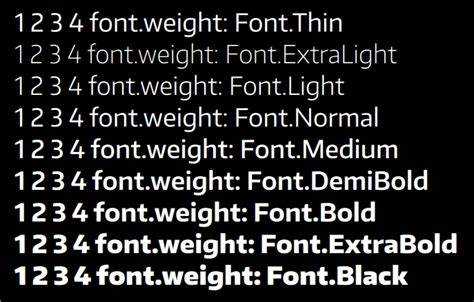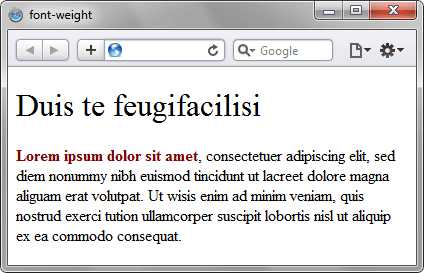
В веб-разработке правильный выбор шрифта играет ключевую роль в восприятии контента. Использование тонких шрифтов, таких как light или thin, может значительно улучшить визуальную привлекательность текста. Чтобы добиться этого эффекта в CSS, важно правильно использовать свойства font-weight и font-family, а также понимать особенности работы с различными типами шрифтов.
Основной метод для создания тонкого шрифта заключается в установке значения font-weight на низкие значения. Для большинства шрифтов значение 100 или 200 будет обеспечивать тонкий, едва заметный стиль. Однако не все шрифты поддерживают такие веса. Например, шрифт Arial не имеет тонкой версии, и применение значения font-weight ниже 400 не даст ожидаемого результата.
Для гарантированного получения тонкого шрифта рекомендуется использовать шрифты, которые включают в себя несколько весов, такие как Roboto, Open Sans или Lato. Эти шрифты имеют отдельные файлы для каждой толщины, что позволяет добиться нужного визуального эффекта. В CSS можно подключить конкретный вес шрифта с помощью свойства font-family и указания нужного веса через font-weight.
Использование свойства font-weight для тонкого шрифта
Свойство font-weight
в CSS позволяет управлять толщиной шрифта. Для создания тонкого шрифта следует использовать значения, которые уменьшают насыщенность линий текста. Это особенно актуально при работе с шрифтами, поддерживающими несколько толщин, таких как Google Fonts или шрифты из семейства OpenType.
Для тонкого шрифта оптимальным значением будет font-weight: 100;
. Оно соответствует самой легкой толщине, которая доступна в большинстве шрифтов. Однако, если шрифт не поддерживает такое значение, можно использовать font-weight: lighter;
, которое сделает шрифт тоньше по сравнению с обычным, но не гарантирует, что результат будет идентичным для всех шрифтов.
Важно помнить, что использование очень тонких шрифтов может снижать читаемость текста на слабых дисплеях или при низком контрасте. Поэтому рекомендуется проверять внешний вид шрифта на разных устройствах и разрешениях. В случае, если шрифт не поддерживает заданную толщину, браузер автоматически применит ближайшее доступное значение.
Для улучшения восприятия тонкого текста на веб-странице можно использовать сочетание font-weight: 100;
с увеличением межстрочного интервала через свойство line-height
. Это сделает текст более четким и читабельным.
Чтобы создать тонкий шрифт в CSS, можно использовать шрифты с нужным начертанием из библиотеки Google Fonts. Эта коллекция предлагает множество шрифтов с разными стилями и толщинами. Чтобы использовать тонкие шрифты, следуйте нескольким ключевым рекомендациям.
- Выбор шрифта. Некоторые шрифты в Google Fonts имеют несколько начертаний, включая ultra-light или thin, которые идеально подходят для создания тонкого текста. Например, шрифт Roboto имеет начертания Thin и Light, а Open Sans – Light и Extra Light.
- Подключение шрифта. После выбора шрифта на сайте Google Fonts необходимо скопировать и вставить ссылку в
вашего документа HTML. Например, для шрифта Roboto с начертанием Thin это будет выглядеть так:
- Применение шрифта в CSS. После того как шрифт подключен, примените его к нужному элементу с помощью свойства
, а также укажите вес шрифта через свойствоfont-weight
. Например:
- Оптимизация производительности. При подключении шрифта из Google Fonts не всегда стоит подключать все доступные начертания, так как это может повлиять на производительность страницы. Лучше выбрать только нужные веса (например, 100 для очень тонкого текста).
- Проблемы с отображением. Некоторые браузеры могут не поддерживать определенные веса шрифтов, поэтому важно проверять внешний вид на разных устройствах и в разных браузерах. В случае проблем попробуйте использовать
с другими значениями.
С помощью Google Fonts можно легко добиться нужного визуального эффекта, выбирая подходящие шрифты и веса, что позволяет создать элегантный и современный дизайн для вашего сайта.
Отличие между нормальным и тонким шрифтом: что нужно знать
Основное различие между нормальным и тонким шрифтом заключается в толщине линий, из которых состоит символ. Тонкий шрифт (например, font-weight: 100
) имеет более легкие линии, что придает тексту воздушность и изысканность. Нормальный шрифт (например, font-weight: 400
) обладает стандартной толщиной, которая подходит для большинства случаев, где важна читаемость и контекстная ясность.
Читаемость: Тонкие шрифты могут ухудшать читаемость при низких разрешениях экрана или на мобильных устройствах, особенно на старых дисплеях. На большом экране или в высококачественных макетах тонкие шрифты могут выглядеть более элегантно, но для текста с плотным контекстом предпочтительнее использовать нормальный шрифт.
Можно ли в CSS сделать шрифт ещё тоньше, чем `font-weight: 100`?
В CSS невозможно задать шрифт тоньше, чем с весом `100`, если сам шрифт не поддерживает более легкие стили. Однако, если вам нужно сделать текст визуально тоньше, можно применить свойство `transform` с масштабированием. Например, `transform: scaleX(0.9);` уменьшит толщину шрифта по горизонтали, что может создать эффект более тонкого текста. Но важно помнить, что этот метод не изменяет фактический вес шрифта, а лишь влияет на его визуальное восприятие. Если же вам нужно использовать более тонкие шрифты, рассмотрите возможность подключения другого шрифта, который имеет нужные веса.